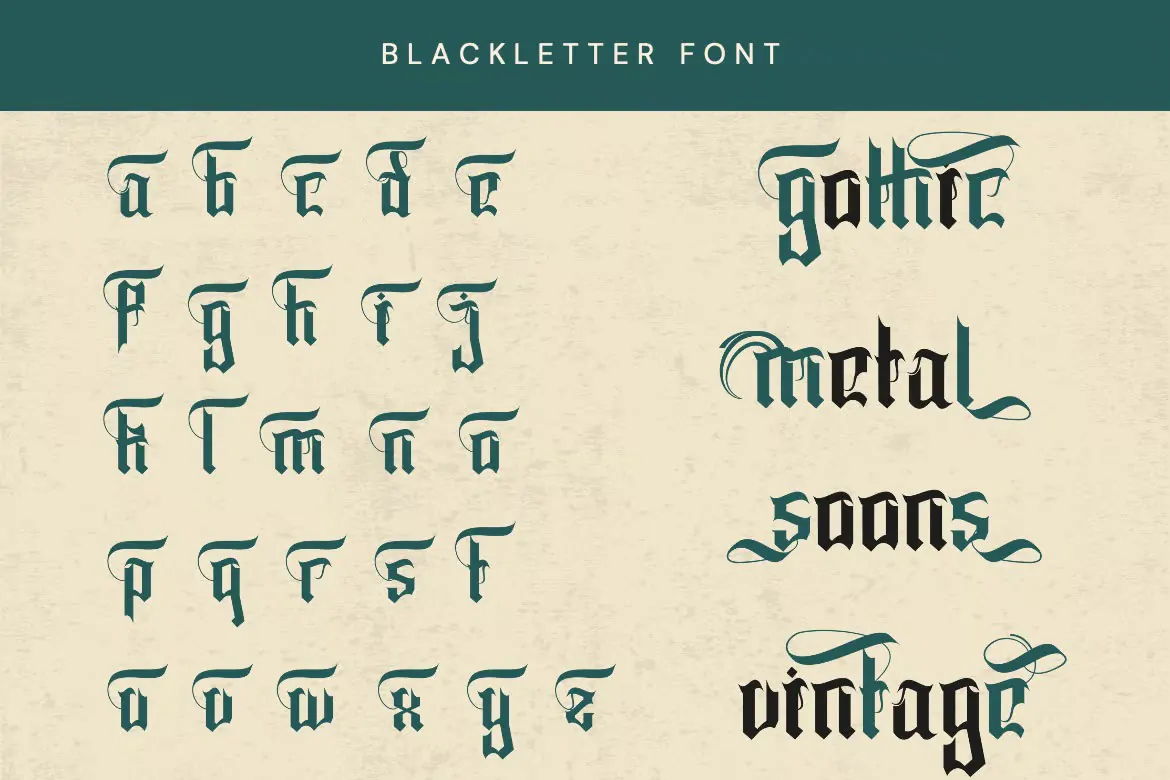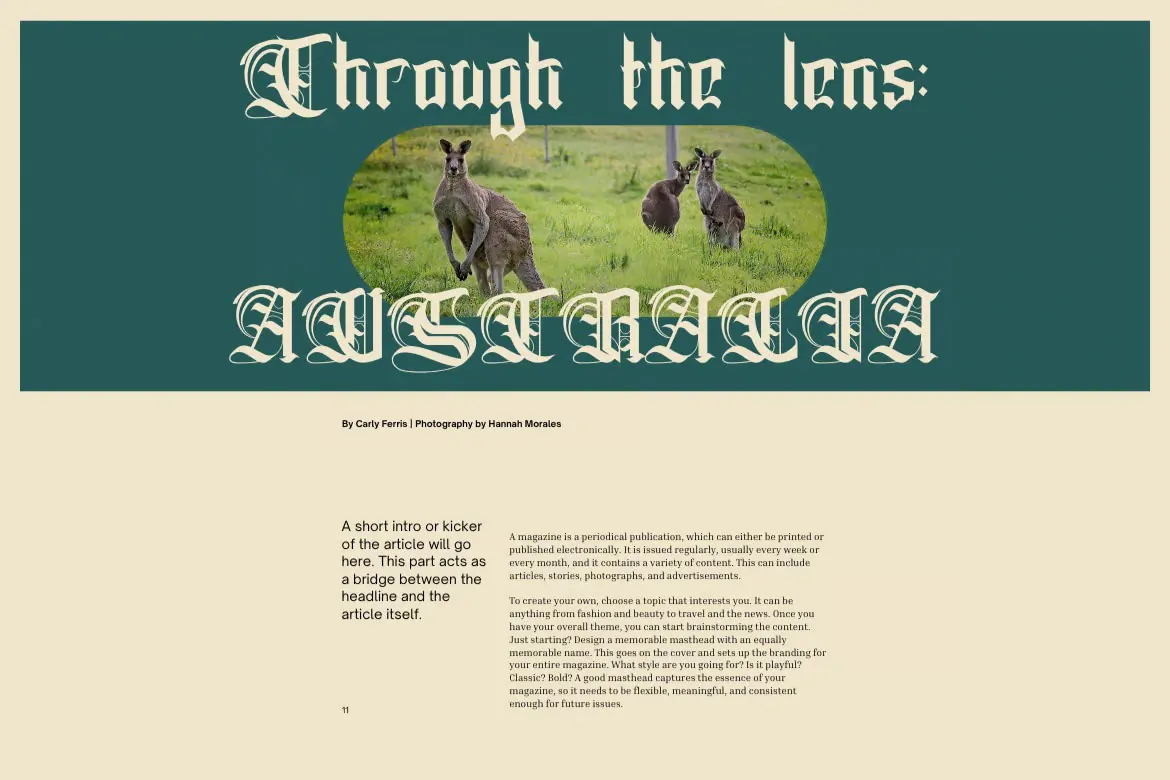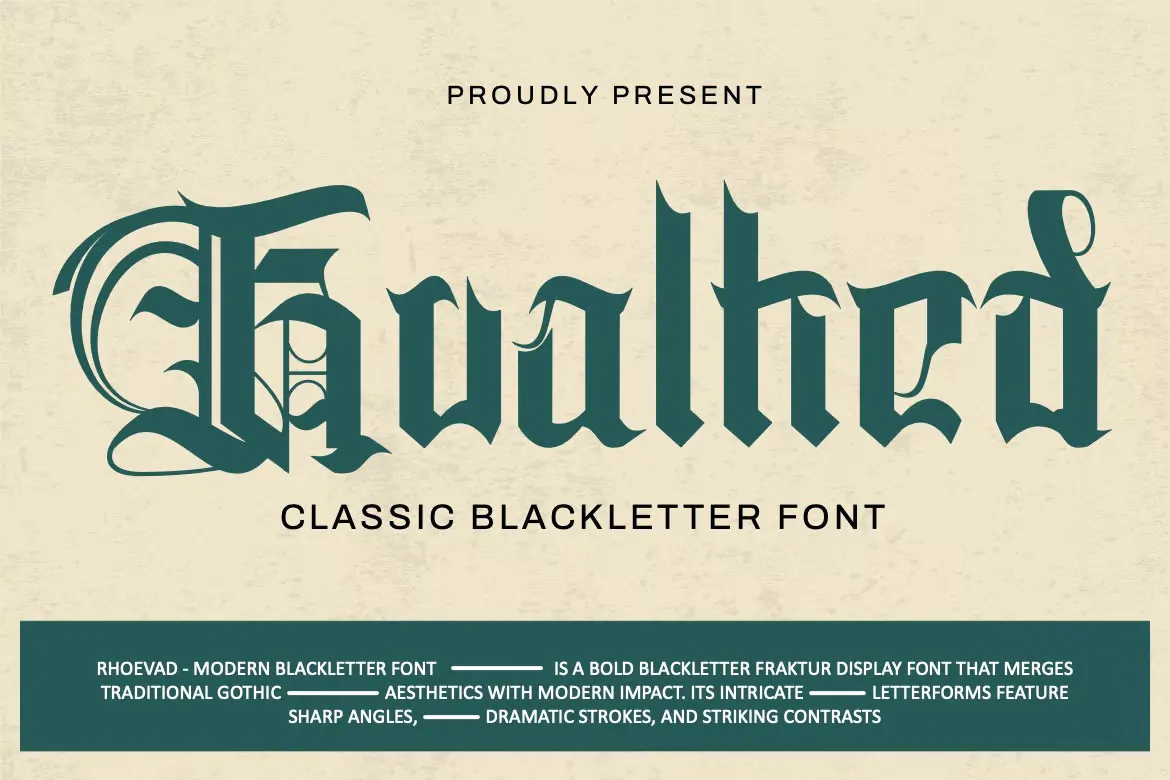
فونت کلاسیک Kualhed
فونت کلاسیک Kualhed یک تایپفیس نمایشی بلکلتر فراکتور با ترکیب ظرافتهای سنتی سبک گوتیک و تأثیرگذاری مدرن است. این فونت با فرمهای پیچیده، زوایای تیز، ضربات پرقدرت و کنتراستهای چشمگیر، حس قدرت، اقتدار و جذابیت تاریخی را منتقل میکند. وزن برجسته این فونت، حضور تأثیرگذاری را در طراحیهای حرفهای ایجاد کرده و آن را به گزینهای ایدهآل برای پروژههایی که نیاز به جلوه جذاب و شیک دارند، تبدیل میکند.
ویژگیها
- حروف: شامل حروف بزرگ و کوچک
- ویژگیهای خاص: دارای حروف جایگزین و لیگاتور
- نمادها و نشانهها: پشتیبانی از شمارهگذاری و نشانهگذاری
- پشتیبانی: چندزبانه
این فونت انتخابی ایدهآل برای طراحیهای حرفهای است.